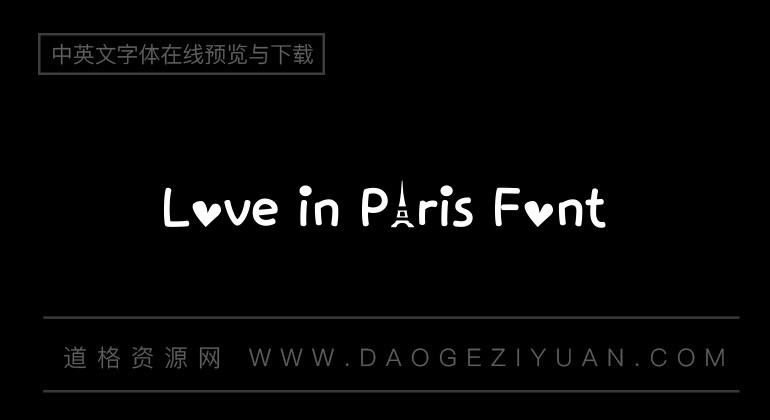
Love in Paris Font 是一款受到巴黎浪漫氛围启发的手写风格字体。该字体的设计师是 Joanne Marie,它结合了浪漫、时尚和优雅的元素,使得这款字体在设计卡片、海报、品牌标志和书籍封面等方面非常受欢迎。 该字体拥有漂亮的连字和细节,形似手写,带有一种现代感和优雅感。Love in Paris Font 适用于多种语言和特殊字符,包括西欧语言、中欧语言和斯堪的纳维亚语言等。 Love in Paris Font 有两种字体风格:常规和粗体,可以根据需要进行选择。这款字体的下载和使用非常方便,可以在多个字体网站上免费下载使用,同时也允许商业用途。内容介绍
Love in Paris Font是一款非常不错的手写艺术字体,具有很好的视觉感,适合于文化类的宣传设计、商业类品牌的广告和产品包装设计以及个性化文字排版等较多场景。